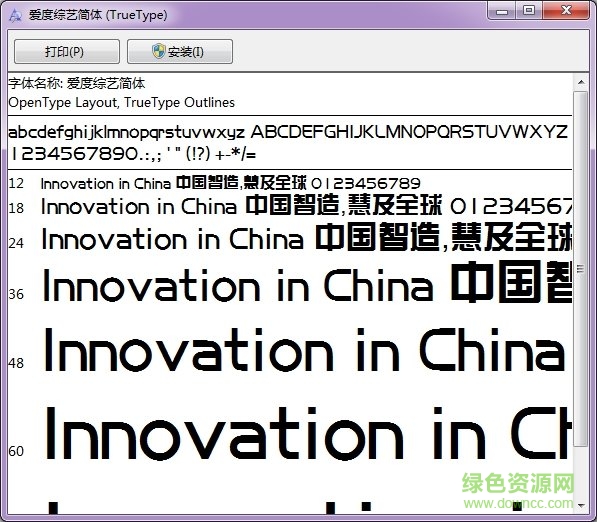
軟件介紹 軟件標(biāo)簽: 綜藝體 廣告字體 adzyjt gb1 0字體就是愛度綜藝簡體,該字體結(jié)合了黑體字體和宋體的特點,具有幾何感,粗細均勻,飽滿大方,符合對稱規(guī)律,適用面廣泛,歡迎大家免費下載!簡體和繁體的區(qū)別繁簡的處理通常是通過改變筆畫細節(jié)加以體現(xiàn),筆畫越是繁瑣或者說結(jié)構(gòu)變化越多,就會更有古典、年代感,反之就會更有現(xiàn)代感。綜藝體推薦dfzongyiw7 授權(quán):免費軟件 WinAll, WinXP, Win7大小:899KB語言:中文dfpzongyiw7字體是使用非常廣泛的一款字體,我們經(jīng)常能在影視作品開頭那些logo字體,還有廣告設(shè)計的大字體看到這個字體,這個字體使用非常的廣泛,而且字體也確實很漂亮,喜歡這個字體的用戶,快來綠色資源網(wǎng)下載吧!下載地址dfpzongyiw9字體 授權(quán):免費軟件 WinAll, WinXP, Win7大小:964KB語言:中文dfpzongyiw9regular字體又叫華康新綜藝體W9,該字體筆劃較粗,骨絡(luò)分明,效果清晰,整體美觀又工整,需要的朋友快來綠色資源網(wǎng)下載吧!dfpzongyiw9字體特點字體特點符合文字含義、具有美觀有趣、易認易識、醒目張揚等下載地址adzyjt--gb1-0字體安裝方法方法一:控制面板/字體/文件/安裝新字體;方法二:直接將字體復(fù)制到C:\WINDOWS\Fonts;方法三:針對win7系統(tǒng),用戶只需選中字體右鍵安裝即可。 軟件截圖 上一張下一張(1 / 1) 安裝詳細截圖 猜你喜歡 綜藝體 綜藝體 綜藝體是一種結(jié)合了宋體和黑體的特點設(shè)計的藝術(shù)字體,線條張揚,邊角圓潤,筆畫粗黑,效果醒目,辨別度極高,適用的范圍也極其廣泛! 查看更多>> 創(chuàng)藝繁綜藝字體 1.31M/中文/0.0/免費版下載 adzyjt--gb1-0字體 900KB/中文/4.4/下載 咸魚綜藝體 869KB/中文/1.6/下載 安托綜藝體 669KB/中文/3.3/下載 緇忓吀緇艱壓浣撶畝字體 1.23M/中文/6.6/下載 愛度綜藝體 869KB/中文/10.0/簡體ttf下載 其他版本下載 標(biāo)題 大小 更新日期 下載 下載地址 電腦版 adzyjt--gb1-0字體 點擊報錯 軟件無法下載或下載后無法使用,請點擊報錯,謝謝! 關(guān)閉報錯反饋 請描述您所遇到的錯誤,我們將盡快予以修正,謝謝! *必填項,請輸入內(nèi)容 本類最新 dreamweaver字體庫 首爾南山體字體 v1.06 官方版 潮字社風(fēng)云簡ttf 潮字社凌渡鯤鵬簡體字體 潮字社曾玉波手書簡字體 微博慧心字體 相關(guān)文章 ADSL 撥號上網(wǎng)為什么要等很長時間 XP系統(tǒng)涌現(xiàn)“內(nèi)存不能為read”毛病 ADSL寬帶上網(wǎng)疑難雜癥會診 如何不用星空極速進行ADSL撥號? ACCESS數(shù)據(jù)庫沒有寫入權(quán)限導(dǎo)致ADODB.Recordset 錯誤 '800a0cb3'的解決辦法 Mysql 安裝問題。提示MySQL Server 5.1 -- Error 1335. 用戶評論 熱門評論 最新評論 發(fā)表評論 查看所有評論(0) 昵稱: 請不要評論無意義或臟話,我們所有評論會有人工審核. 字?jǐn)?shù): 0/500 (您的評論需要經(jīng)過審核才能顯示)